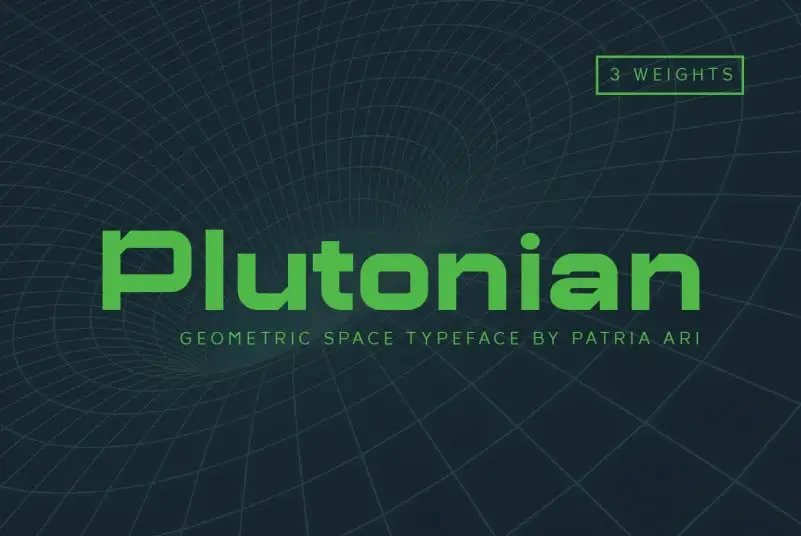
Plutonian Font – Download Grátis
A fonte Plutonian é inspirada nas formas geométricas simples encontradas nos temas aeronáuticos espaciais, criada pelo designer Patria Ari Typestudio. Este tipo de fonte apresenta três pesos diferentes e foi projetada para ser fácil de usar em uma ampla gama de aplicações como logotipos, títulos, capas de revistas, headlines, templates PowerPoint e identificação visual de placas. Com sua base geométrica única, Plutonian se destaca não apenas por sua simplicidade e modernidade, mas também pela capacidade de se adaptar a diversas necessidades gráficas. Esta fonte é uma excelente escolha para designers de todos os níveis que procuram um tipo de letra resistente e versátil, capaz de dar vida ao seu trabalho em diversos formatos e ambientes.